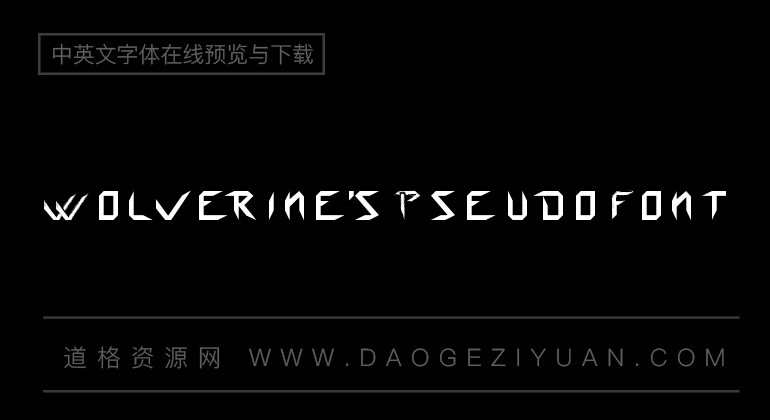
Wolverine's Pseudo Font 是一种装饰性的英文字体,它模仿了金属切割的效果,给人一种坚强、刚毅的感觉。这种字体的特点是每个字母都有一个或多个切割痕迹,类似于金属表面被切割或雕刻的效果,因此它看起来非常有力量和决心。 此字体的字母形状较为简洁,每个字母的线条粗细不一,有的线条较为粗壮,有的线条则细小。此外,此字体的大部分字母都带有切割痕迹,添加了一些有趣的纹理和细节,增加了字体的视觉效果和吸引力。 Wolverine's Pseudo Font 可以用于设计海报、广告、标志、标题、宣传单页等等需要强烈视觉效果和决心感的场合。内容介绍
Wolverine's Pseudo Font是一款非常不错的手写艺术字体,具有很好的视觉感,适合于文化类的宣传设计、商业类品牌的广告和产品包装设计以及个性化文字排版等较多场景。